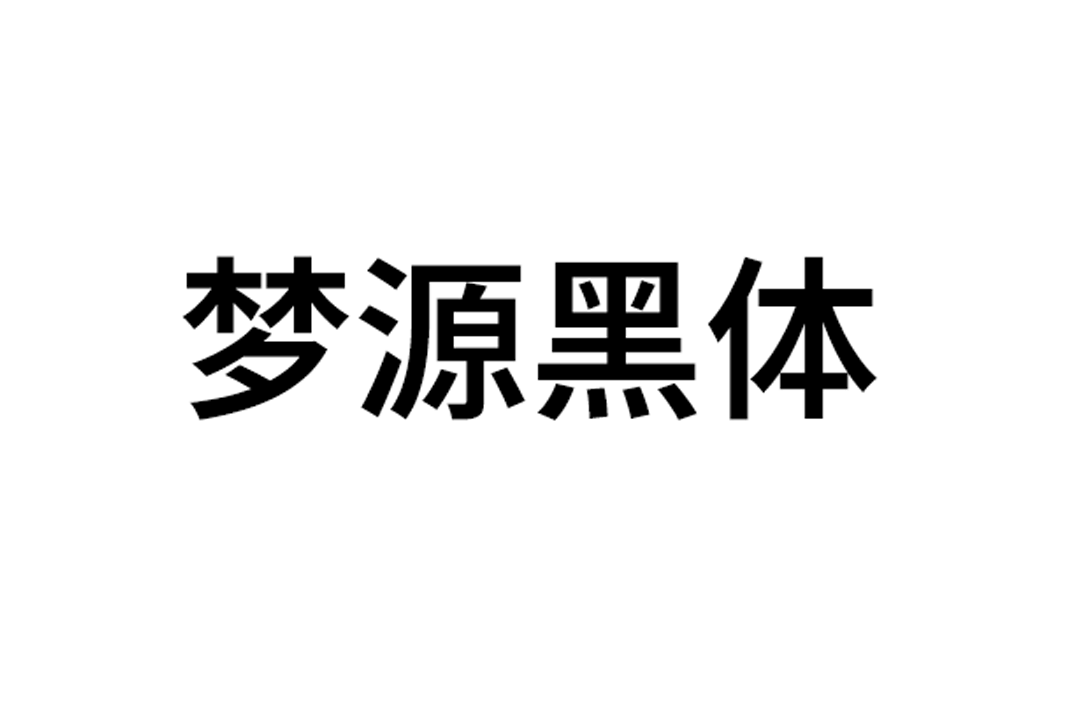
梦源黑体以可变版思源黑体为母版,将可变版思源字体的大量中间字重实例化为传统单字重字体,合并了重叠的曲线轮廓,在保证最大兼容性的前提下,提供更加细腻、丰富的字重选择。此外,本项目修复了思源系列广泛存在的 Adobe 行高过大问题。本系列字体的其他功能(如字形、竖排、kerning、多语言、异体字、曲线精度等)与思源系列保持完全一致,未做任何修改。
名称语言特点
DreamHanSans完整版6,5535 字符,含所有语言/地区字形
DreamHanSansCN大陆简体中文子集只包含简中标准字形
DreamHanSansHK香港繁体中文子集只包含香港标准字形
DreamHanSansTW台湾繁体中文子集只包含台湾国字标准字形
DreamHanSansJP日本语子集只包含日本标准字形
DreamHanSansKR韩国语子集只包含韩国标准字形,又称为“旧字形”
字体特点:
● 样式:W1 - W27 共计 27 字重
● 字符集:完整版含 6,5535 字符
● 异体字支持:简、台繁、港繁、日、韩
● OpenType 功能(竖排支持等):完整收录,与思源系列相同
● Adobe 行高:标准行高,已修复思源系列存在的行高过大问题
● Microsoft Office Style-Link:加粗按钮 B 链接黑体的 W12 与 W22 字重,以及宋体的 W7 与 W20 字重
● 曲线格式:二次贝塞尔曲线
● 曲线精度(UPM, units per em):2048,即原版 OpenType/CFF 三次曲线的无损转换
● 屏显渲染策略:全字号亚像素抗锯齿(Windows 10 及更新版本)